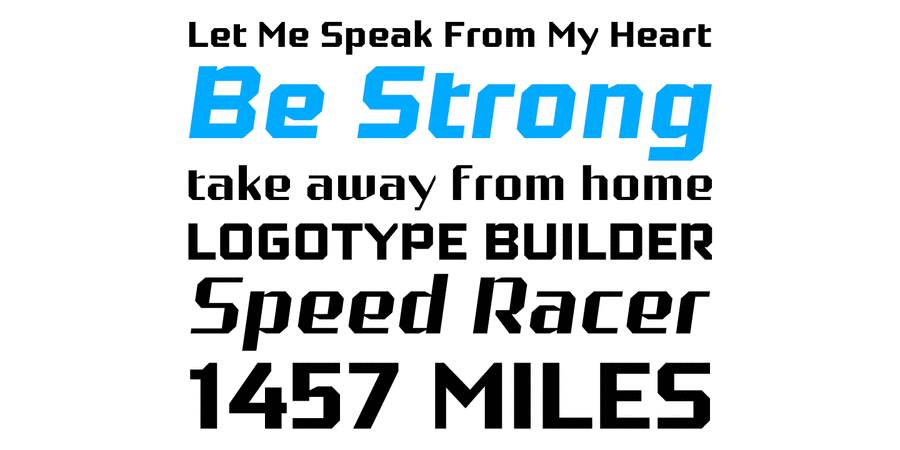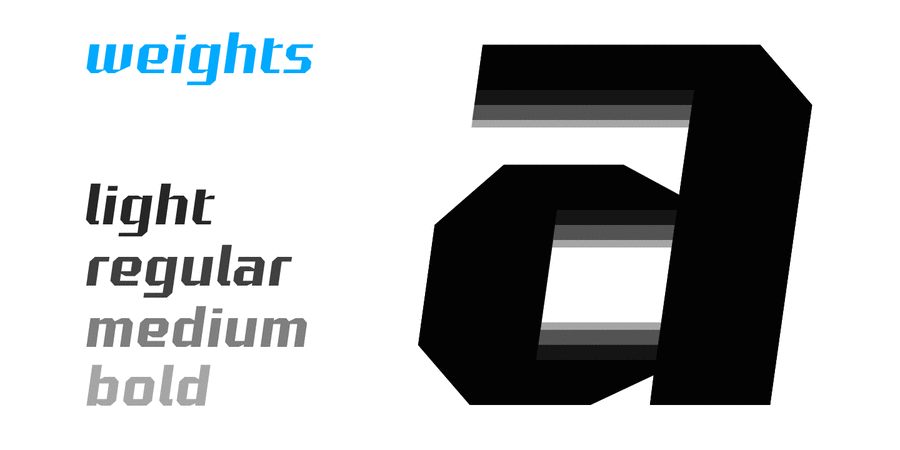
Опис гарнітури Robotesqa 4FИдея создания шрифта Robotesqa 4F пришла в 2010 году в процессе дизайна интерфейса компьютерной игры (неопубликованной), а именно экранной статистики о прохождении уровней. Все символы латиницы и кириллицы создан в 2010 году, а остальные – в конце 2013 года, включая стрелки, иконки и прочее. Также были добавлены стилистические альтернативы, с более закрытой апертурой. Шрифт Robotesqa 4F выпущен Сергеем Ткаченко в 2013 году.
Особливості сімейства шрифтів Robotesqa 4FХіт десятиліття:
Хіт 1980-х Схожий на шрифти з логотипів, ігор, фільмів:
LEGO Nexo Knights
Асоціації з сімейством шрифтів Robotesqa 4FОсобистість і характер гарнітури:
комп'ютерний, електронний, молодіжний, рівний, квадратний, точний, логічний, холодний, автоматичний, техногенний, твердий, статичний, різкий, чіткий, стійкий, стабільний, прямокутний, міський, сучасний, машинний, інженерний, урбаністичний, креслярський, надійний, впевнений, сталевий, космічний, переконливий, серйозний, сильний, індустріальний, залізний, мужній, військовий, армійський, промисловий, спортивний, залізничний, футуристичний, ламаний, незграбний, помітний, яскравий, активний, робочий, кінематографічний, гранчастий, ігровий, хлоп'ячий, рубаний, сміливий, швидкий, гоночний, швидкісний, мотивуючий, суворий, гучний, крутий, амбітний, потужний, значний, грубий, брутальний
код, комп'ютер, конструктор, креслення, інженер, автоматика, урбаністика, електроніка, авто, інструмент, робот, гра, космос, промисловість, війна, армія, зброя, завод, металургія, верстат, тара, склад, порт, ящик, патрони, техніка, прилад, ремонт, депо, шолом, уніформа, вагон, авіація, літак, автомат, шутер, екшен, спорт, машинобудування, охорона, захист, паливо, транспорт, страйкбол, поліція, будівництво, будматеріали, взуття, цегла, технології, андроїд, залізо, фантастика, залізниця, робочий, кіно, лего, іграшка, кубики, кіберспорт, комп'ютерна гра, селфі, гонки, швидкість, ралі, Доставка, супергерой, тренажери, електростанція, енергетика, блокбастер, бойовик, сталевар, мотор, двигун, далекобійник, вантажівка, екскаватор Гарнітура асоціюється з віком: